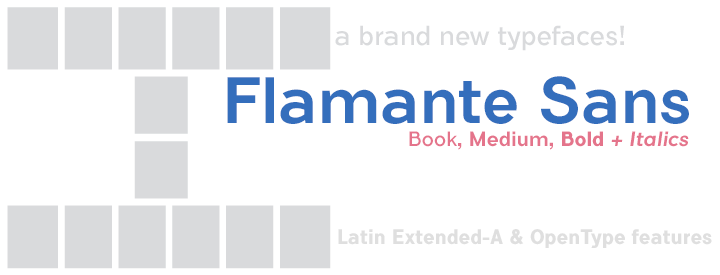
Se dice de las letras sin remates, también se conocen como grotescas, buenos ejemplos son la Helvetica o Univers, el conocido diseño suizo desarrollo profusamente este tipo de fuentes, convirtiendose hoy en una opción muy usada.
J.M. Nexus Grotesque es el fruto de la amistad entrañable entre dos viejas conocidas tipografías de aspecto grotesco, una de ellas flaca, la otra gorda, una ergida, la otra tumbada. Homenaje a dos fuentes clásicas de épocas diferentes pero que comparten ADN tipográfico suficiente para crear un nueva typeface que servirá perfectamente en diseño gráfico …
Esta nueva tipografía se trata de una fuente comprimida de estilo modernista y romántico y sin serif, inspirada en tipografías decorativas de los principios del S.XX. El diseño de la fuente está realizado para usarla en tamaños por encima de los 24pt, es una tipografía de proporciones heavy y comprimida, y su utilización óptima en …